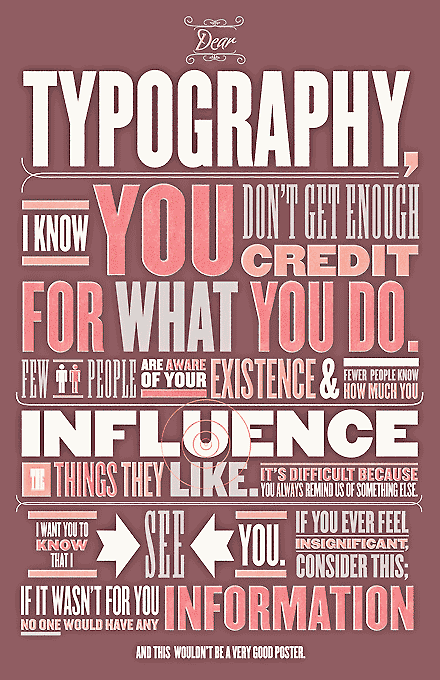Tipografia
Tipografia
1. Aspecto Historico
1. Concepto
1. Letra: signo; representación gráfica del lenguaje hablado. Evolución de la escritura.
1. Tipografía: es el arte de diseñar letras y componer texto de tal modo que puedan leerse de un modo fácil, eficaz y agradable.
2. Partes de una letra
1. Asta: Rasgo principal de la letra que la define como su forma o parte más esencial.
1. Astas montantes: Son las astas principales u oblicuas de una letra, tales como la “L,B,V”
1. Anillo: Es el asta curva cerrada que forman las letras “b, p y o”
1. Brazo: Parte terminal que se proyecta horizontalmente o hacia arriba y que no se encuentra incluida dentro del carácter, tal como ocurre en las letras “E, K o L”
1. Cola: Asta oblícua colgante en dirección descendente que forman algunas letras como la “R o K”.
1. Ascendente: Asta que contiene la letra de caja baja y que sobresale por encima de la altura de caja baja, las letras tales como: “b, d y k”.
1. Descendente: Asta de la letra de caja baja que se encuentra por debajo de la línea base, como ocurre con la letra “p” o “g”
1. Línea base: línea sobre la que se apoya la altura.
1. Ojo: El espacio en blanco que queda en el interior de las letras.
2. Variables visuales Amplitud. (hace referencia a la extensión de la letra).
1. Forma: relativo a la estructura
1. Tamaño: definido por altura / cuerpo
1. Inclinación: (hace referencia a la inclinación de los ejes de la letra). Las letras pueden ser derechas (redondas) o inclinadas11 (cursivas)
1. Posters Con Tipografia
1. Tipografia como Forma